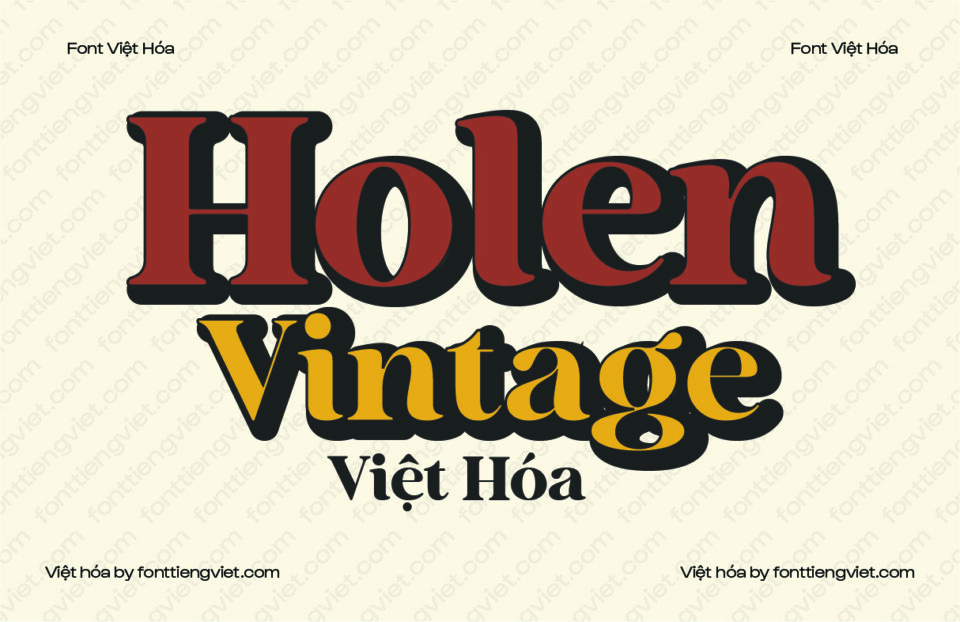
Giới thiệu bộ Font việt hóa 1FTV VIP Holen Vintage đầy ấn tượng
Trong thế giới đồ họa hiện đại, việc lựa chọn Font Chữ đóng vai trò quan trọng để tạo nên linh hồn cho sản phẩm. Font việt hóa 1FTV VIP Holen Vintage là một bộ phông đặc biệt dành cho những ai yêu thích vẻ đẹp hoài cổ nhưng vẫn giữ được nét tinh tế, sang trọng. Được phát triển dựa trên cảm hứng từ những bảng hiệu quảng cáo xưa, bộ font này mang đến cảm giác gần gũi và đầy tính nghệ thuật. Đối với các bạn học sinh hay thầy cô giáo, đây là lựa chọn tuyệt vời để trang trí slide bài giảng hoặc thiết kế bìa sách thêm phần bắt mắt.
Tại sao bạn nên chọn Font việt hóa 1FTV VIP Holen Vintage?
Đặc điểm nổi bật nhất của Font việt hóa 1FTV VIP Holen Vintage chính là sự tỉ mỉ trong từng đường nét. Các ký tự được chăm chút kỹ lưỡng để đảm bảo khả năng hiển thị tiếng Việt hoàn hảo, không bị lỗi dấu – một vấn đề thường gặp ở các font ngoại nhập. Với phong cách Serif mạnh mẽ kết hợp cùng các đường cong mềm mại, bộ font này cực kỳ phù hợp cho các thiết kế logo, poster sự kiện trường học hay các thiệp mời mang hơi hướng vintage.
Cách sử dụng Font việt hóa 1FTV VIP Holen Vintage hiệu quả nhất
Để tận dụng tối đa vẻ đẹp của font, bạn nên kết hợp nó với những gam màu trầm như nâu đất, vàng nghệ hoặc xanh rêu. Điều này giúp tôn lên chất “cổ” đặc trưng. Ngoài ra, việc điều chỉnh khoảng cách giữa các chữ cái cũng giúp bố cục trở nên thoáng đạt và dễ đọc hơn trên cả màn hình máy tính lẫn bản in thực tế.